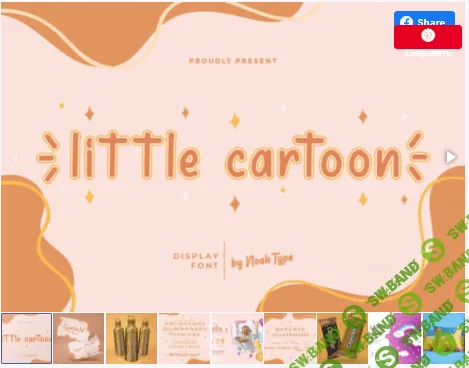
Название: Little Cartoon Font (2022)
Little Cartoon — забавный дисплейный шрифт с простым стилем, вдохновленным комиксами. Little Cartoon Font обладает уникальным эксклюзивным стилем. Этот удивительный сценарий предназначен для всех, кому нужна веселая, смелая и стильная типографика.
Little Cartoon Comic Font отлично подойдет для приглашений, мероприятий, фильмов, музыки, детских книг, школы, детских товаров, социальных сетей и т. д.